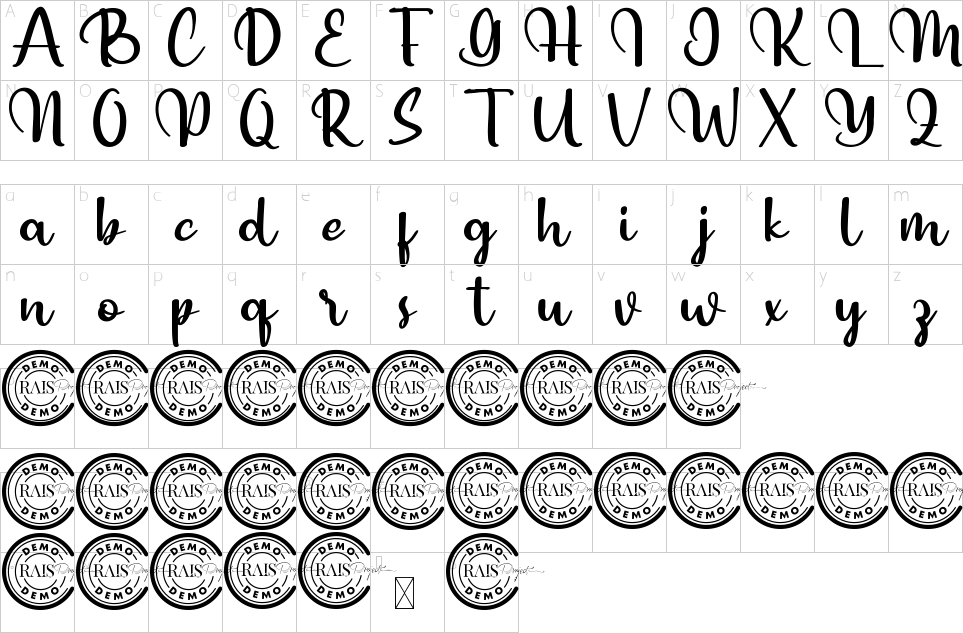
Aqui está uma descrição em português do Brasil, envolvente e natural, para uma página de download da fonte ‘Malven Hills Font | 1001 Free Fonts’: A Malven Hills font é uma escolha perfeita para designers gráficos que buscam uma fonte clara e elegante. Desenhada pelo designer anônimo que criou essa fonte, a Malven Hills oferece um equilíbrio entre seriedade e modernidade. Perfeita para uso em identidades digitais, gráficos de e-mail e até mesmo em títulos de slides de apresentação, ela traz um ar de sofisticação sem ser excessivamente formal. Com um design fluido e minimalista, a Malven Hills é uma fonte versátil que irá destacar seu trabalho, seja em projetos profissionais ou pessoais. Se você está procurando por uma fonte grata para seu projeto, a Malven Hills pode ser uma ótima escolha. Com uma fácil integração em qualquer projeto digital, ela certamente deixará seu trabalho ainda mais profissional.